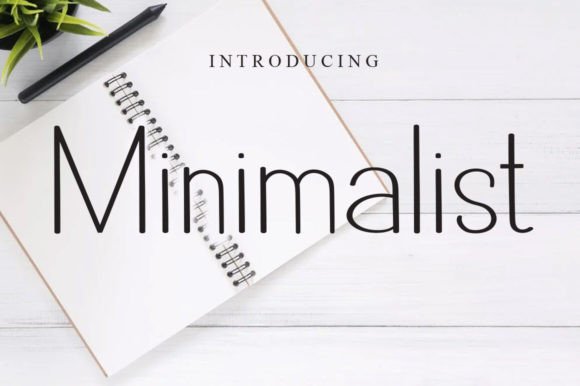
Minimalist
適切なデザイン要素を見つけるのは難しい場合がありますが、Minimalistは作品を即座に引き立てる優れたコレクションを提供します。
POD(オンデマンド印刷)製品、結婚式の招待状、またはソーシャルメディアのグラフィックを作成している場合でも、Minimalistは理想的です。